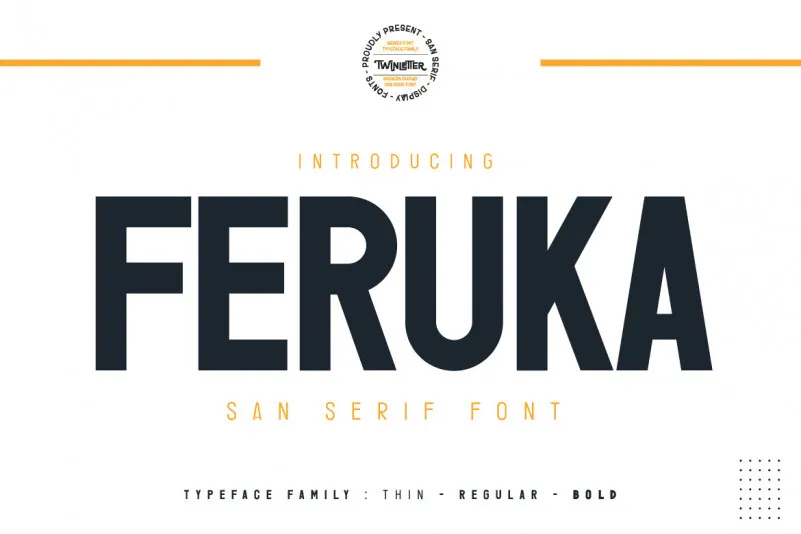
Feruka Font – Download Grátis
A fonte Feruka é uma escolha inegável para qualquer designer que busca uma solução clara e moderna para seus projetos. Embora seja uma fonte tipo sans serif, ela carrega um poderoso jeito de expressão graças ao seu estilo marcante e personalidade valente. Esta font oferece não apenas versões regular e bold, mas também variações estreitas que permitem a simplicidade necessária para atender às demandas dos seus projetos. Com uma aplicação capaz de dar um boost visual inegável aos designs, Feruka é perfeita para transmitir mensagens fortes aos consumidores em cada projeto. É uma escolha ótima para aquelas produções que buscam destaque e simplicidade ao mesmo tempo. Seja em uma banner de marketing ou em um logotipo criativo, esta font ajuda a destacar seu design sobre qualquer outra opção.